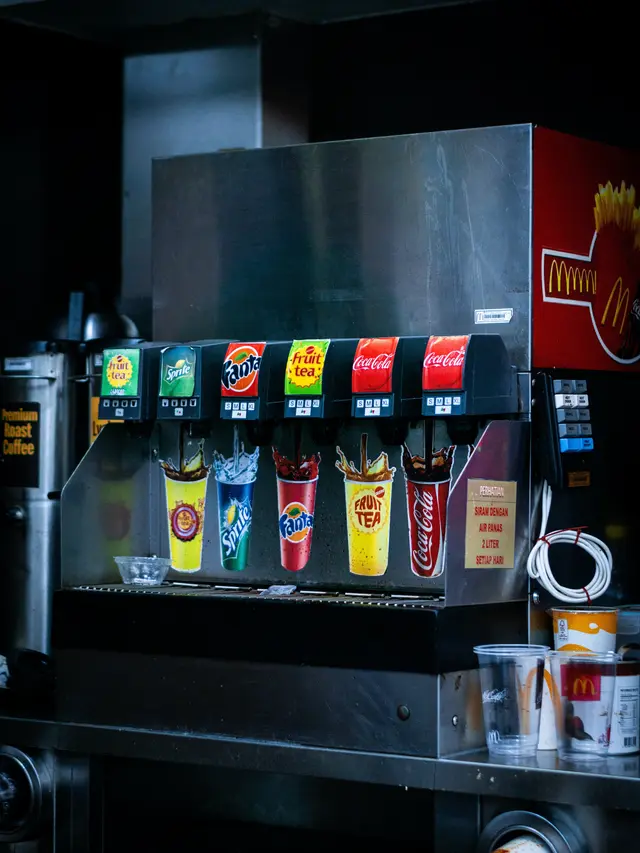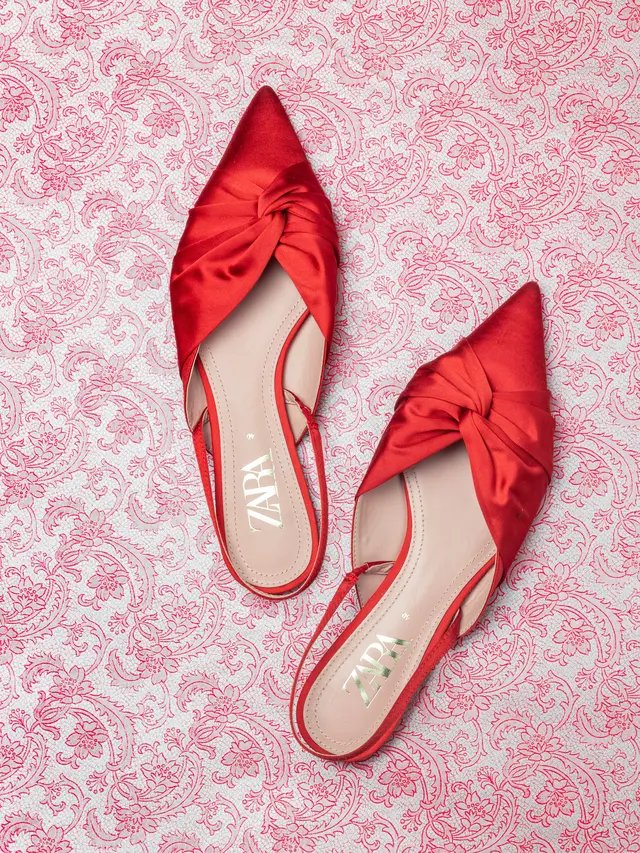
Liputan6.com, Jakarta Memahami apa saja jenis font keren ini berguna dalam proses desain dan promosi. Ada lima jenis font keren yang paling sering digunakan. Apa saja?
Melansir dari Tailor Brands, pada Selasa (25/1/2022) lima jenis font keren tersebut adalah font serif, sans serif, slab serif, skrip, dan dekoratif. Dari lima jenis font keren ada fungsi secara psikologis yang perlu dipahami sebelum memilih menggunakannya.
“Semua jenis font ini menawarkan karakteristik unik dan memainkan peran penting dalam makna simbolisnya cocok pada desain logo akhir Anda,” dijelaskan.
Merek terkenal yang menggunakan lima jenis font keren adalah Zara, Tiffany & Co, LinkedIn, Coca-cola, The Guardian, Sony, Honda, Lego, hingga Fanta. Berikut Liputan6.com ulas lebih mendalam tentang penjelasan lima jenis font keren dan fungsinya, Selasa (25/1/2022).
1. Font Serif
Font serif adalah jenis font keren dan tertua. Jenis font keren serif pertama kali digunakan pada akhir abad ke-15. Kata 'serif' mengacu pada kaki kecil yang ada di bagian atas dan bawah setiap huruf. Bunga kecil ini berasal dari kuas seniman dan akan ditambahkan ke huruf sebagai elemen dekoratif.
Jenis font keren serif ada banyak tipenya. Ada Gaya Lama, Klasik, Neo-Klasik, Transisi, Clarendon, dll. Saat ini, jenis font keren Serif adalah salah satu tipografi paling populer yang digunakan, dengan gaya seperti 'Times New Roman' yang selalu ada di buku, dokumen, dan bahkan beberapa logo.
Merek terkenal yang menggunakan jenis font keren serif adalah Zara, Tiffany & Co, Abercrombie & Fitch.
Secara psikologi, fungsi jenis font keren serif adalah menggambarkan merek yang elegan dan canggih. Logo dengan tipe ini menampilkan suasana tradisi, kehormatan, dan keandalan.
Jenis font keren serif diandalkan untuk membantu perusahaan tampak lebih mapan dan ideal untuk mengomunikasikan identitas berdasarkan otoritas dan keagungan. Organisasi di bidang akademik, editorial, dan keuangan menyukai font serif berkat penampilan konservatif dan terhormatnya.
2. Font Sans Serif
Font Sans Serif adalah jenis font keren yang memiliki ciri khas lebih bersih dan modern. Adanya ciri khas ini membuat jenis font keren san serif cocok disandingkan dengan jenis font keren serif.
Jenis font keren sans serif ada sejak abad ke-19 dan menjadi sangat populer di tahun 1920-an dan 30-an. Selama pertengahan abad ke-20, desainer Jerman semakin memperbanyak jenis huruf dengan penciptaan desain Helvetica yang populer.
Adanya jenis font keren ini terbentuk oleh garis-garis yang bersih dan lurus. font sans serif tidak mudah dibaca dan modelnya lebih sederhana. Tipe jenis font keren sans serif ada cukup banyak. Mulai dari gaya Grotesque, Square, Geometric, dan Humanistic.
Merek terkenal yang menggunakan jenis font keren sans serif adalah LinkedIn, Calvin Klein dan The Guardian.
Secara psikologis, fungsi jenis font keren Sans Serif adalah menawarkan tampilan yang bersih atau simpel dan tanpa basa-basi. Jenis font keren sans serif mampu memberikan penekanan dengan pendekatan berpikiran maju.
Jenis font keren sans serif tampak berani dan cocok untuk menarik perhatian, berkat desainnya yang halus dan efisien. Perusahaan yang memilih keluarga font ini memprioritaskan rasa kepekaan dan kejujuran yang tidak perlu berkembang atau bakat.
3. Font Slab Serif
Font slab serif adalah jenis font keren yang termasuk variasi tipografi serif tradisional. Jenis font keren slab serif pertama kali ditemukan pada abad ke-19. Tipografi ini berani. Kaki yang menentukan font serif lebih besar dan seperti blok (terlihat seperti "lempengan").
Jenis font keren slab serif memiliki ciri-ciri lebih solid, berani, dan lebih cocok dengan merek modern daripada yang klasik. Font slab serif dapat berbentuk bulat atau bersudut, dengan beberapa gaya mesin tik yang sangat mirip.
Merek terkenal yang menggunakan jenis font keren slab serif adalah Sony, Honda, dan Volvo.
Secara psikologis, fungsi jenis font keren slab serif adalah tentang gambar yang keras dan berani. Jenis font keren slab serif mampu menyampaikan rasa percaya diri, ketergantungan, dan pemikiran kreatif berkat garis berat serta tidak terlalu halus.
Merek terkenal yang menggunakan jenis font keren slab serif adalah guna menunjukkan betapa inovatifnya ide dan produk yang ditawarkan. Adanya jenis font keren slab serif dapat membantu mengkomunikasikan rasa penting dan membutuhkan.
4. Font Skrip
Font skrip adalah jenis font keren yang membawa gaya skrip kasual dan mulai populer di abad ke-20. Jenis font keren skrip mendukung gaya kursif yang tampak lebih alami. Skrip muncul dalam dua sub-kategori utama, yakni formal dan kasual.